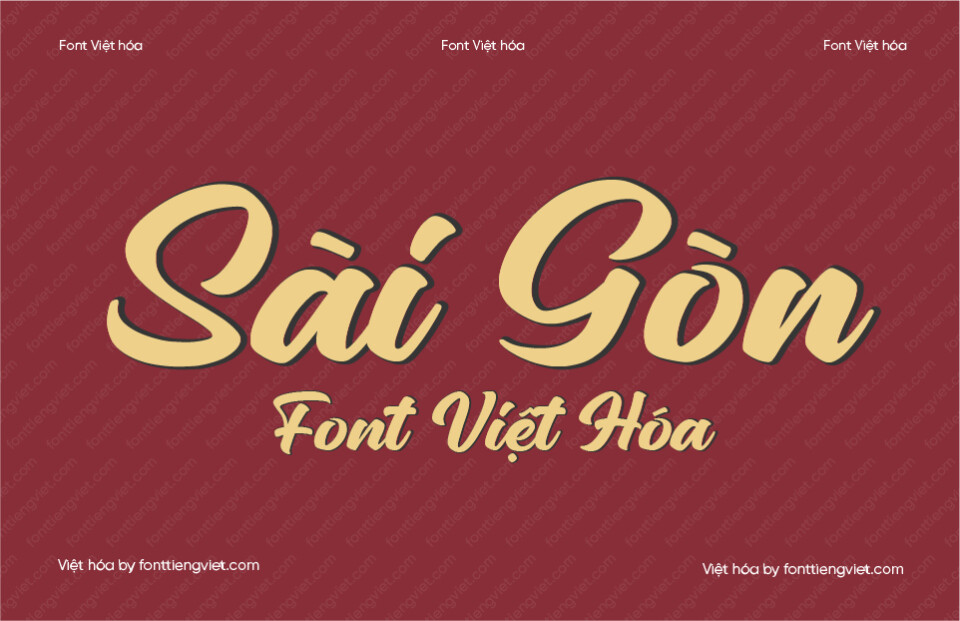
Giới thiệu về Font Việt hóa 1FTV VIP Sinethar – Font Vintage
Trong thế giới thiết kế đồ họa hiện nay, việc lựa chọn một bộ Font Chữ phù hợp đóng vai trò quyết định đến tính thẩm mỹ của sản phẩm. Font Việt hóa 1FTV VIP Sinethar – Font Vintage là một tác phẩm nghệ thuật chữ viết mang phong cách cổ điển, quý phái và đầy tinh tế. Được chăm chút tỉ mỉ từng đường nét, bộ font này tái hiện vẻ đẹp của những thập niên trước, mang lại cảm giác hoài niệm nhưng không kém phần sang trọng cho người xem.
Đặc điểm nổi bật của bộ font
Bộ Font Việt hóa 1FTV VIP Sinethar – Font Vintage nổi bật với những đường cong uốn lượn mềm mại và cấu trúc chữ thanh thoát. Đây là lựa chọn lý tưởng cho các bạn học sinh, sinh viên khi thực hiện các dự án thiết kế thiệp mời, bìa sách hoặc poster chủ đề lịch sử. Sự kết hợp giữa nét chữ truyền thống và kỹ thuật việt hóa chuẩn xác giúp người dùng dễ dàng sử dụng trong các phần mềm phổ biến mà không lo lỗi dấu hay khoảng cách chữ.
Ứng dụng thực tế và cách sử dụng hiệu quả
Khi sử dụng Font Việt hóa 1FTV VIP Sinethar – Font Vintage, bạn nên chú ý phối hợp với các tông màu trầm như nâu đất, vàng đồng hoặc đỏ rượu để làm nổi bật tinh thần vintage. Font chữ này cực kỳ phù hợp cho các tiêu đề lớn, tạo điểm nhấn thị giác mạnh mẽ. Trong môi trường giáo dục, thầy cô có thể dùng font này để trang trí bảng tin hoặc thiết kế slide bài giảng về văn học, giúp bài học trở nên sinh động và lôi cuốn hơn đối với học sinh.
Kết luận về bộ font chữ đẹp